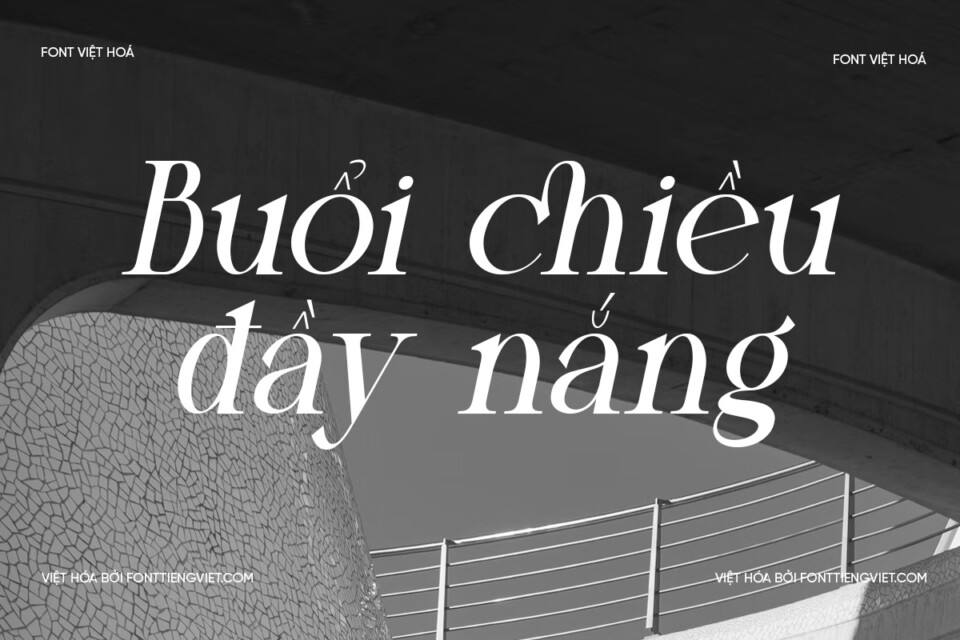
Font Việt hóa 1FTV VIP Lorenna Italic
Font Việt hóa 1FTV VIP Lorenna Italic: Sự Lựa Chọn Sang Trọng Cho Thiết Kế Việt
Giới thiệu về Font Việt hóa 1FTV VIP Lorenna Italic
Trong thế giới thiết kế đồ họa hiện đại, việc tìm kiếm một bộ Font Miễn Phí chất lượng cao và hỗ trợ đầy đủ tiếng Việt là ưu tiên hàng đầu của nhiều nhà sáng tạo. Một trong những cái tên đang gây chú ý gần đây chính là Font Việt hóa 1FTV VIP Lorenna Italic. Đây là một bộ font chữ mang phong cách Italic (nghiêng) đầy thanh lịch, tinh tế và cực kỳ sang trọng. Được tinh chỉnh kỹ lưỡng bởi đội ngũ 1FTV, bộ font này không chỉ đảm bảo tính thẩm mỹ mà còn khắc phục hoàn toàn các lỗi hiển thị dấu câu trong tiếng Việt, giúp người dùng tự tin thể hiện ý tưởng trên mọi nền tảng số.
Đặc điểm nổi bật của Lorenna Italic
Font Việt hóa 1FTV VIP Lorenna Italic nổi bật với những đường nét uyển chuyển, mềm mại nhưng vẫn giữ được cấu trúc rõ ràng. Kiểu dáng Italic đặc trưng tạo cảm giác chuyển động nhẹ nhàng, phù hợp cho các tiêu đề tạp chí, thiệp mời đám cưới, hoặc các ấn phẩm quảng cáo cao cấp. Khả năng hiển thị sắc nét trên cả màn hình máy tính lẫn bản in giúp nó trở thành công cụ đắc lực cho các bạn học sinh, sinh viên khi làm báo cáo hoặc bài thuyết trình cần sự chuyên nghiệp và khác biệt.
Ứng dụng thực tế của Font Việt hóa 1FTV VIP Lorenna Italic trong thiết kế
Việc sử dụng Font Việt hóa 1FTV VIP Lorenna Italic giúp nâng tầm giá trị hình ảnh cho mọi dự án. Với phong cách Serif cổ điển kết hợp biến tấu hiện đại, bộ font này thường được ưu tiên trong các lĩnh vực như thời trang, làm đẹp và nội thất. Dưới đây là một số ứng dụng cụ thể mà bạn có thể tham khảo:
• Thiết kế Logo và Brand Identity: Tạo điểm nhấn độc đáo cho thương hiệu cá nhân với những đường nét nghiêng nghệ thuật.
• Thiết kế Poster và Banner: Giúp các thông điệp quảng cáo trở nên thu hút và bắt mắt hơn nhờ sự thanh mảnh của nét chữ.
• Trang trí thiệp chúc mừng: Mang đến cảm giác ấm áp, chân thành và đầy trang trọng cho người nhận.
Lợi ích khi sử dụng font chữ đã Việt hóa
Sự khác biệt lớn nhất khi bạn chọn Font Việt hóa 1FTV VIP Lorenna Italic chính là sự đồng bộ. Thay vì lo lắng về việc các ký tự có dấu như “ă, ê, ô, ơ” bị lỗi font hoặc nhảy chữ, phiên bản VIP này đã được tối ưu hóa 100%. Điều này giúp quy trình thiết kế diễn ra trôi chảy, tiết kiệm thời gian chỉnh sửa thủ công và đảm bảo thông điệp được truyền tải một cách trọn vẹn nhất tới người xem.
Để tận dụng tối đa vẻ đẹp của bộ font này, người dùng cần lưu ý một số kỹ thuật nhỏ khi trình bày. Font Việt hóa 1FTV VIP Lorenna Italic hoạt động tốt nhất khi được kết hợp với các font chữ không chân (Sans-serif) đơn giản để tạo sự tương phản. Bạn có thể sử dụng nó cho các đoạn trích dẫn ngắn hoặc tiêu đề chính để tạo điểm nhấn thị giác mạnh mẽ.
Lưu ý khi phối màu và bố cục
Vì đây là kiểu chữ có nét thanh nét đậm rõ rệt, bạn nên sử dụng các gam màu tối trên nền sáng hoặc các tông màu Pastel để tôn lên sự quý phái. Tránh nhồi nhét quá nhiều chữ trong một không gian hẹp, hãy để các ký tự có khoảng thở để người đọc dễ dàng cảm nhận được sự tinh tế của từng nét chữ.
Kết luận về bộ Font Việt hóa 1FTV VIP Lorenna Italic